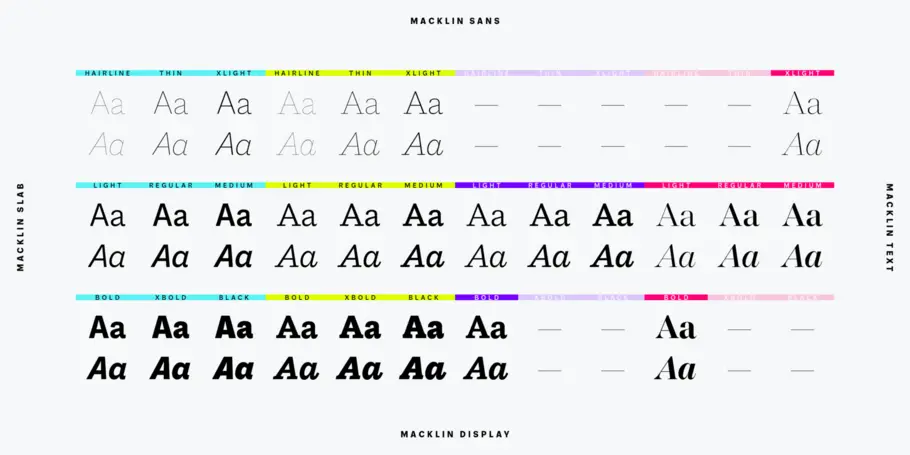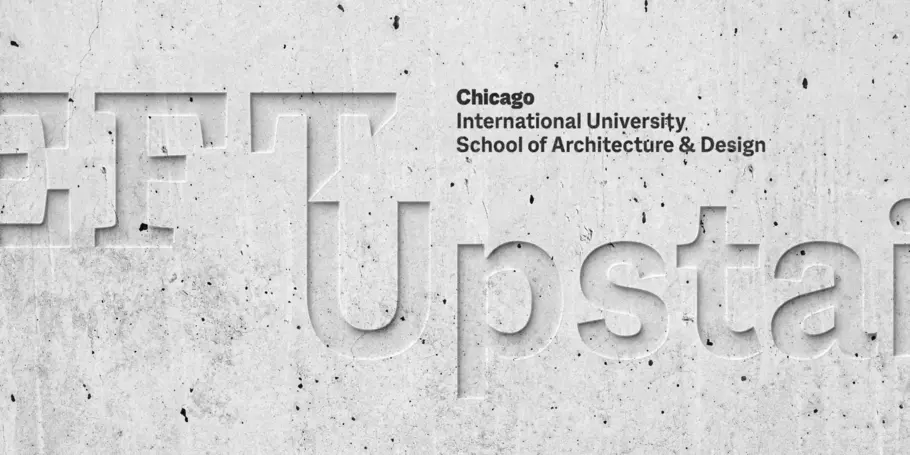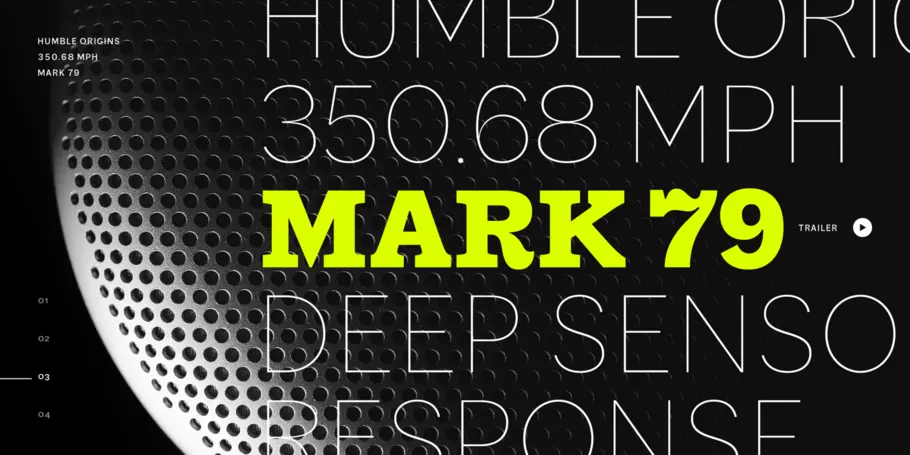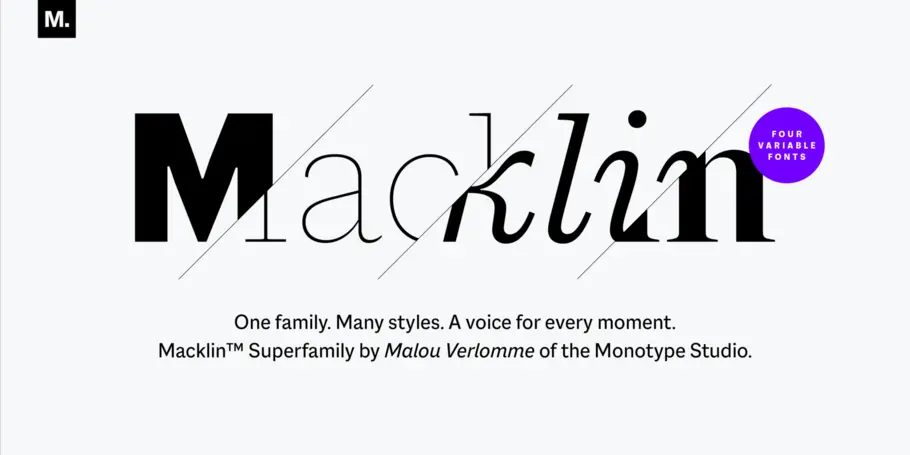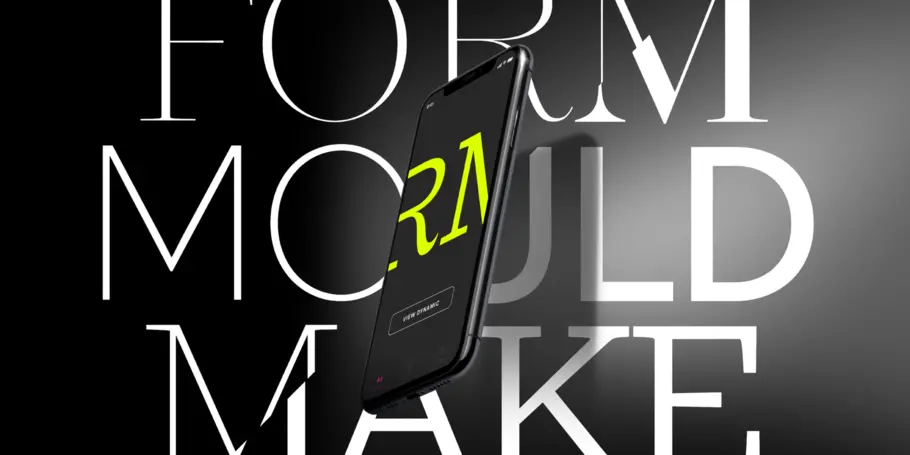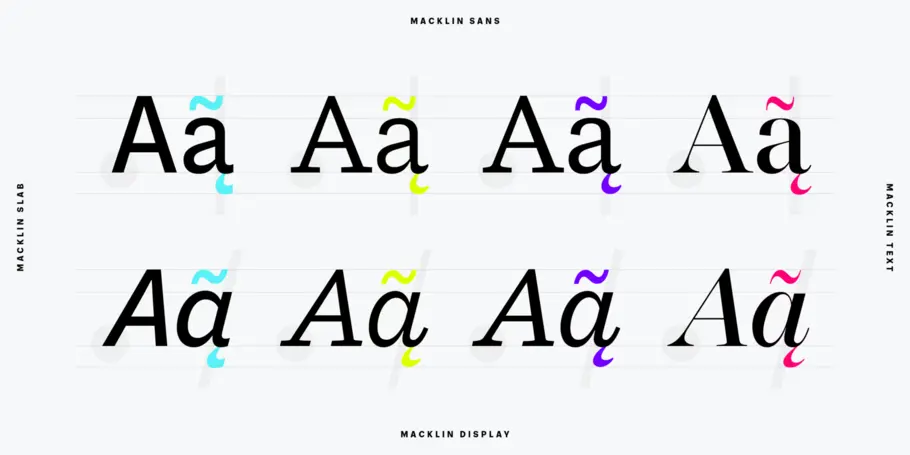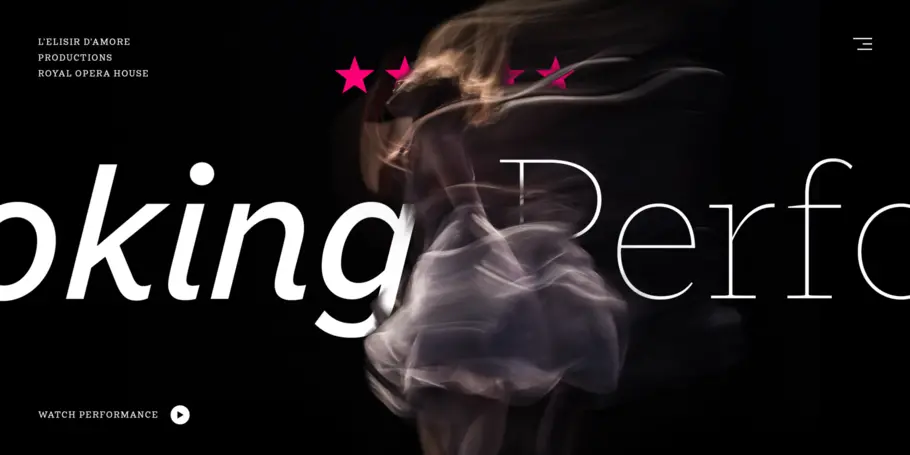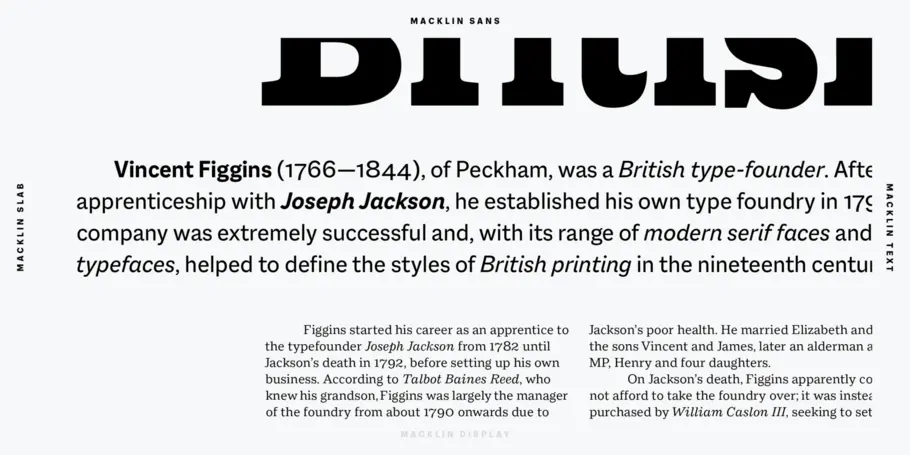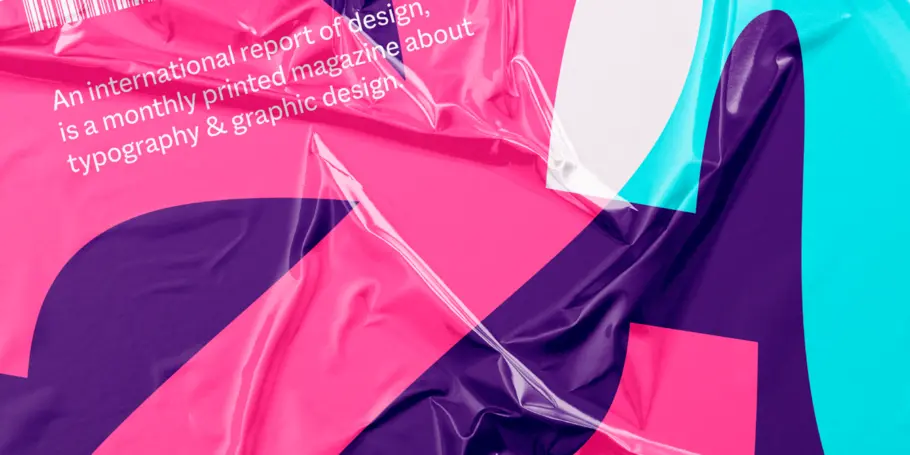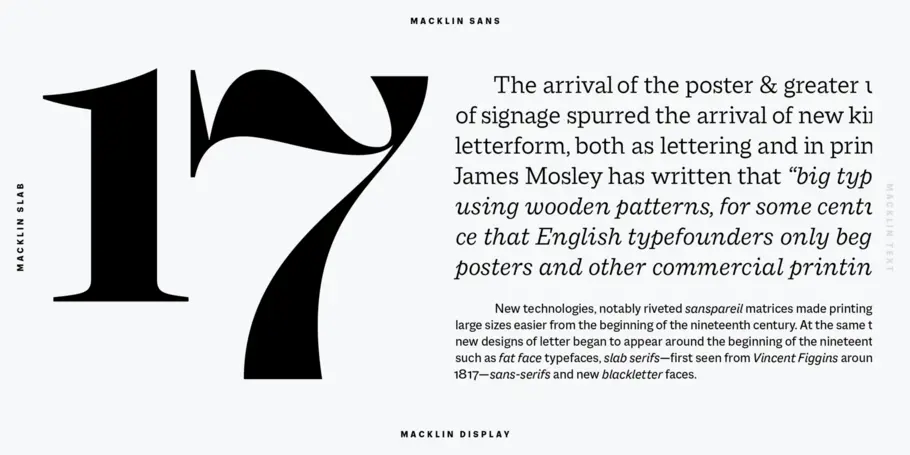
Macklin™
Inspiré par l’histoire. Créé pour le design contemporain.
Macklin s’inspire de l’époque où la typographie est passée des pages de livres aux affiches et aux publicités. Avec une nette évolution par rapport à ses prédécesseurs, les formes pures et élégantes de Macklin rendent la superfamille adaptée au design contemporain. Macklin comprend 4 sous-familles et 54 fontes avec 9 graisses allant du Hairline au Black, offrant une large palette d’expression visuelle.
Malou Verlomme is Senior Type Designer for Monotype, and has been with the company since 2016. His Camille typeface has the honor of being part of the collection at France’s Centre National des Arts Plastiques (CNAP).